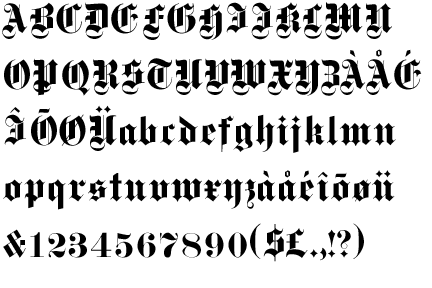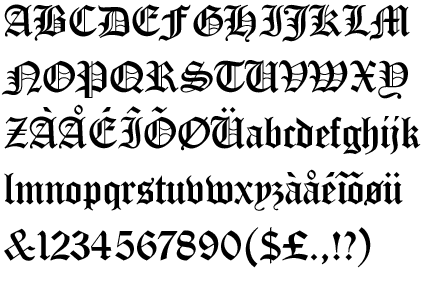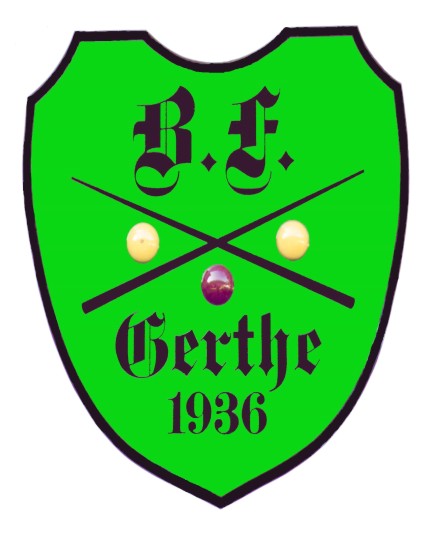
Suche die Schriftart aus einem Vereins Emblem
Kann mir jemand helfen würde gerne das Emblem neu gestalten, aber mit der gleichen Schriftart.
Schriften dieser Art sind ab der zweiten Hälfte des 18ten Jh. in England geschnitten worden. Hier mal der Eintrag zur Old English auf Identifont: Based on Caslon Black, a Blackletter type cast by the William Caslon foundry in England around 1760.
Old English
Based on Caslon Black, a Blackletter type cast by the William Caslon foundry in England around 1760.
Designer: Monotype Staff
Year: 1994
Publishers: ITC and Letraset
In der zweiten Hälfte des 19ten Jh, wurden die so richtig modisch und nach 1900 gab es dann die Schriften wie wir sie heute kennen von den großen Schriftgießereien: Old English, Engravers Old English, Marriage ... Damit wird die Suche schon etwas einfacher. Einfach mal auf Identifont.com gehen, Old English suchen und dann ein bisschen durch die ähnlichen Schriften klicken bis man auf was Passendes trifft. Und dabei immer schön daran denken: Die Schrift im Logo wurde sehr wahrscheinlich zusammengestaucht und läuft bei artgerechter Haltung weiter. Das Suchen geht ziemlich schnell und ich stelle Dir die 3 Minuten nicht in Rechnung.
Gothique
Publishers: Monotype Imaging and Mecanorma
Das scheint eine relativ neue Schrift zu sein.